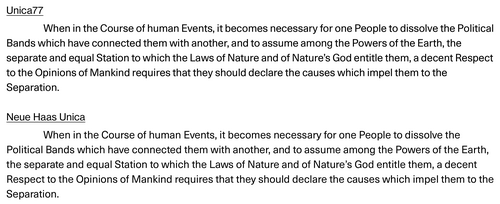
يونيكا (نوع الخط)
يُعدّ خط Unica أو Haas Unica خطًا جديدًا من نوع sans-serif ، طُوّر في شركة Haas Type Foundry أواخر سبعينيات القرن الماضي، وأُصدر لأول مرة عام ١٩٨٠. بدأ المشروع بهدف الجمع بين مزايا خطي Helvetica و Univers ، إلا أنه للأسف صدر للطباعة الضوئية في وقتٍ كانت فيه هذه التقنية تُصبح قديمةً بفعل النشر المكتبي ، كما حالت عمليات الاندماج اللاحقة ونزاع حقوق النشر دون طرح نسخة رقمية منه في السوق. في عام ٢٠١٥، أُعيد إصدار نسختين رقميتين منه: إحداهما من قِبل أصحاب الحقوق، والأخرى بموافقة الفريق الذي طوّره في الأصل.
النسخ الأصلية
في عام ١٩٧٢، استحوذت شركة هاس لطباعة الخطوط (سويسرا) ، التي أُغلقت لاحقًا، على منافستها الفرنسية ديبرني وبينو ، التي كانت تمتلك حقوق نشر خط يونيفرس . وبذلك، أصبحت هيلفيتيكا (المعروفة أيضًا باسم نيو هاس غروتسك) ويونيفرس ملكًا للشركة نفسها منذ ذلك الحين. خلال سبعينيات القرن العشرين، قررت هاس طرح نسخة محدثة من هيلفيتيكا للطباعة الضوئية الإلكترونية على الشاشة . أُسندت المهمة إلى فريق ٧٧ (أندريه غورتلر، وكريستيان مينغلت ، وإريك غشويند). وكانت النتيجة خطًا هجينًا يجمع بين هيلفيتيكا ويونيفرس بشكل أساسي ، وهو ما أكسبه اسم يونيكا (وهو مزيج من كلمتي Uni vers وHelvetica ) ، ولكنه تضمن أيضًا خصائص خطوط أخرى، مثل أكزيدنز غروتسك . [ 1 ] [ 2 ] تم إصدار Unica في عام 1980. وبسبب ظهور برامج النشر المكتبي ونزاع الملكية، اختفى الخط بسرعة كبيرة من السوق.
إصدار رقمي
حتى عام ٢٠٠٨، كان هناك إصدار رقمي متاح من Scangraphic في متجر الخطوط التابع لشركة Elsner+Flake، ولكن تم سحب هذا الإصدار من السوق بعد أن طالبت شركة Linotype بحقوق الطبع والنشر لشركة Haas Type Foundry المتوقفة عن العمل. ونظرًا لعدم توفر الخط قانونيًا، أصبحت تفاصيله التقنية غير واضحة. ومع ذلك، يُعتقد أن لهذا الخط حجمين بصريين، هما SB ( Scangraphic Body؛ مصمم لنصوص المتن) وSH (Scangraphic Headline؛ مصمم للعناوين والصفحات). [ ٣ ] يتميز Unica SH بتباعد أحرف أضيق من Unica SB.
الإحياءات الحديثة
يونيكا إنترميديت (غير منشور)
هذا العمل المُعاد إنتاجه، والذي ابتكرته لويز باراديس، لم يُطرح للجمهور قط. [ 4 ] [ 5 ]
نوي هاس يونيكا (2014-2015)
صممه توشي أوماغاري لشركة مونوتيب، وهو عبارة عن إحياء يعتمد على ملفات الطباعة الضوئية Unica الخاصة بفريق '77 الموجودة في أرشيف مونوتيب في ألمانيا. [ 6 ]
تتضمن عائلة الخطوط 9 أوزان بعرض واحد، مع خطوط مائلة مكملة، ليصبح المجموع 18 نمطًا. لا تدعم هذه العائلة النقاط المستديرة، ولكنها تدعم الأحرف الصغيرة. كما يتوفر من خط Neue Haas Unica إصدار Paneuropean (W1G) الذي يدعم الأحرف اليونانية والسيريلية . يُباع إصدار Neue Haas Unica Paneuropean بشكل منفصل عن الإصدار الأساسي. [ 7 ]
LL Unica77 (2015-2016)
هذا إحياءٌ للتصميم الأصلي من سبعينيات القرن الماضي. وقد أُنشئ بالتعاون بين موريس غولدنر وكريستيان مينغلت (الذي كان عضوًا في فريق 77 وأذن بتطبيق هذا الخط Unica) لصالح دار الطباعة السويسرية Lineto . [ 8 ] ووفقًا لمصمم الخط، ألبرت-يان بول ، فإن Lineto (على عكس Monotype) تدفع رسوم ترخيص لفريق 77. [ 9 ] يستخدم هذا الإصدار بدائل أسلوبية لتقديم نسخة بنقاط دائرية وعلامات ترقيم.
تضمنت النسخة الأولية الصادرة في 7 مارس 2015 ثمانية خطوط بأربعة أوزان (خفيف، عادي، غامق، أسود) وعرض واحد، مع خطوط مائلة مكملة. وفي فبراير 2016، أُضيفت ستة خطوط بثلاثة أوزان إضافية (رفيع، متوسط، أسود فاحم). أما فيما يتعلق بدعم اللغات، فيوفر Unica77 أربعة إصدارات، هي: اللاتينية، والسيريلية، واليونانية، و"عموم أوروبا".
الاختلافات بين نوي هاس يونيكا ويونيكا 77
تتشابه تصميمات حروف خطي Neue Haas Unica وUnica77 إلى حد كبير، إذ يستند كلاهما إلى خط Haas Unica الأصلي. مع ذلك، توجد بينهما بعض الاختلافات الطفيفة: يتميز Unica77 بارتفاع حرف x أكبر قليلاً من Neue Haas Unica؛ وبنفس الوزن وحجم الخط، يتميز Unica77 بتباعد أضيق بين الحروف افتراضياً، كما أن حروفه أثقل من حروف Neue Haas Unica. تبرز هذه الاختلافات بشكل أوضح عند استخدام نصوص طويلة بحجم صغير.
يحتوي رمز اليورو في خط Neue Haas Unica على نهايات أفقية كما هو الحال في خط Helvetica (Neue Haas Grotesk)، بينما يحتوي الرمز الموجود في خط Unica77 على نهايات رأسية كما هو الحال في خطي Univers وNeue Helvetica.